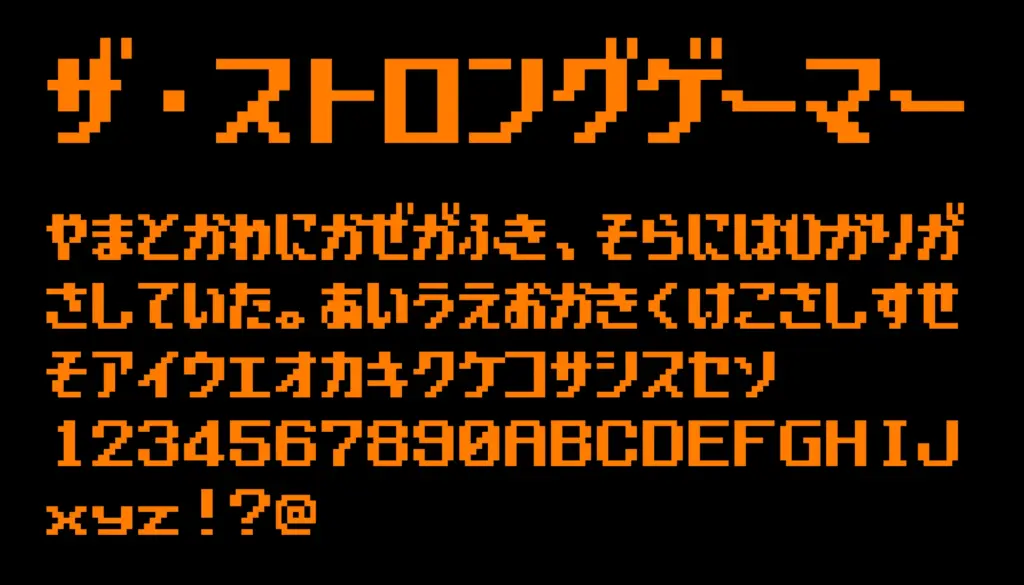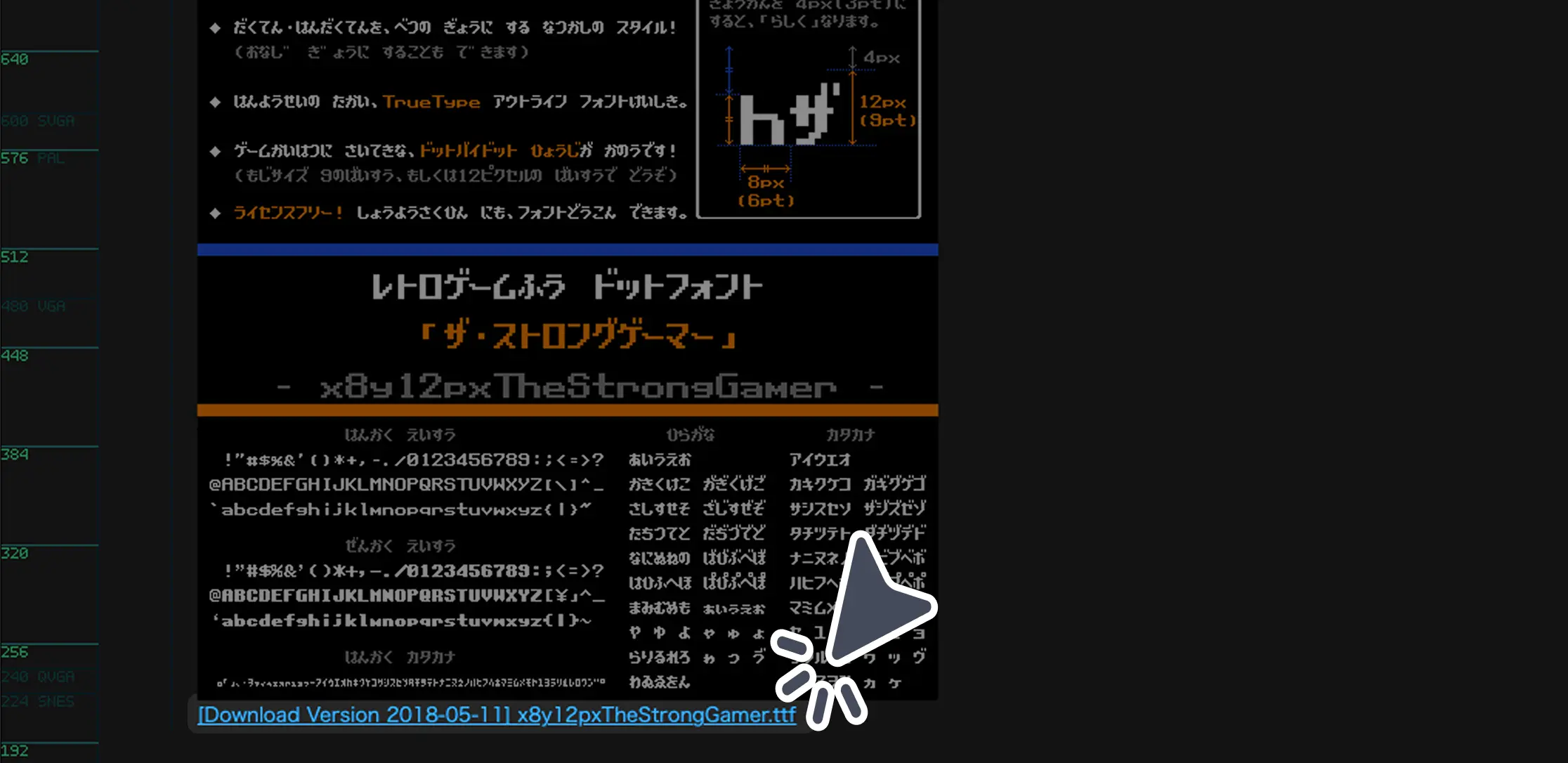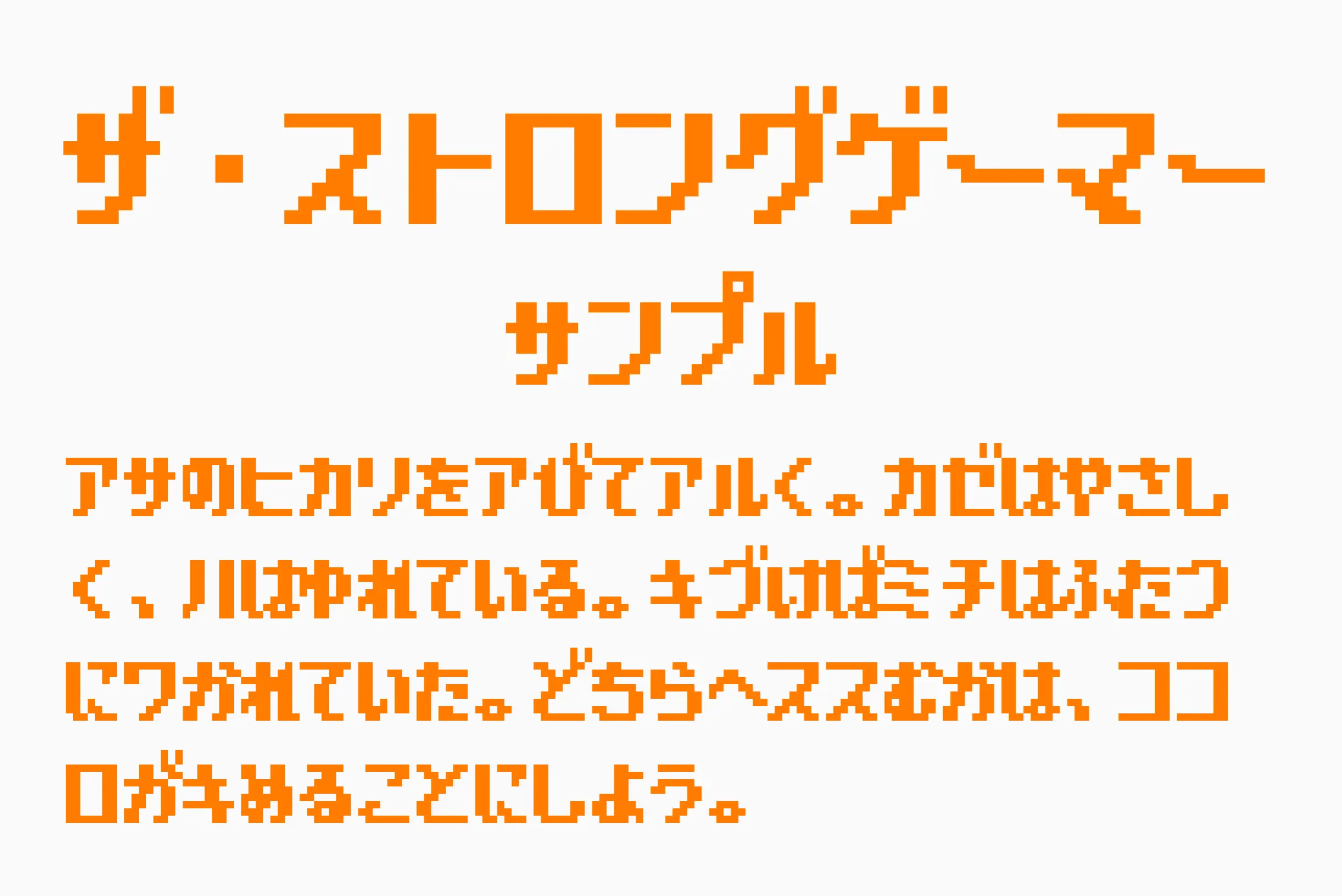
太くて重厚なデザインが特徴のタイトル向けフリーフォント。角ばったフォルムとインパクトのあるシルエットで、まさに“強さ”や“迫力”を演出したい場面に最適です。ゲーム実況動画のロゴやサムネイル、eスポーツ系バナー、イベント告知などにぴったりの存在感です。
ザ・ストロングゲーマー
| 収録文字 | ひらがな・カタカナ・英字・数字・記号 |